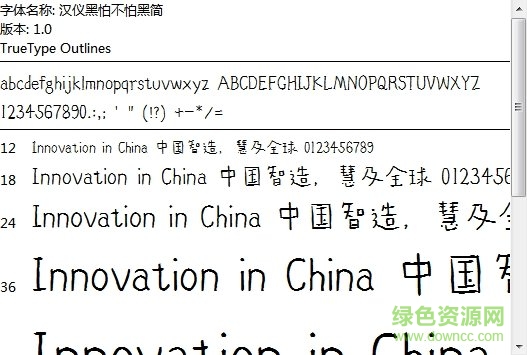
漢儀黑怕不怕黑簡(jiǎn)
黑怕不怕黑字體是漢儀字庫(kù)推出的一款手寫字體,專為紅花會(huì)黑怕不怕黑打造,字跡扁長(zhǎng)而清瘦,端正而嚴(yán)明,讓你的設(shè)計(jì)更有增色,快來(lái)綠色資源網(wǎng)免費(fèi)下載吧!
漢儀黑怕不怕黑字簡(jiǎn)特色
黑怕不怕黑體,隸屬于漢儀字體,中文字體比較窄長(zhǎng),有著極佳的閱讀體驗(yàn),英文端正清晰,讓人眼目一新,十分適合平面設(shè)計(jì)、藝術(shù)設(shè)計(jì)、包裝設(shè)計(jì)等場(chǎng)合使用。